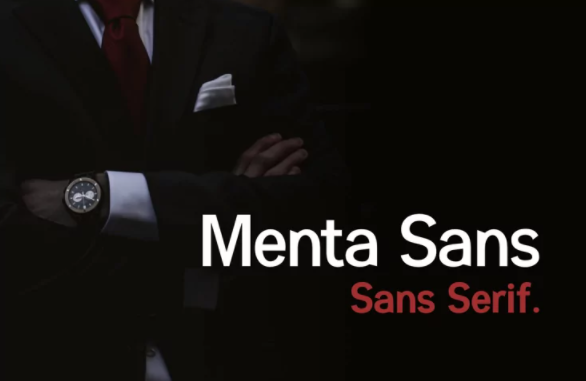
Menta Sans - элегантный шрифт Sans Serif, созданный компанией Dumadistyle. Благодаря естественному и современному стилю, этот шрифт идеально подходит для оформления ваших проектов. Menta Sans был создан, чтобы помочь вам улучшить качество вашего дизайна, особенно в брендинге вашей компании. Этот шрифт включает 6 семейств шрифтов: Regular, Italic, Thin, Thin Italic, Bold, Bold Italic, с верхним и нижним регистром.
Шрифт Menta Sans имеет современный стиль, который идеально подходит для различных целей дизайна, таких как логотипы, заголовки, обложки книг, брендинг, цитаты, реклама, обложка фильма, название компании, заголовок и многое другое. Посмотрите превью выше, чтобы подобрать подходящий вариант для вашего проекта. Оставайтесь стильными!